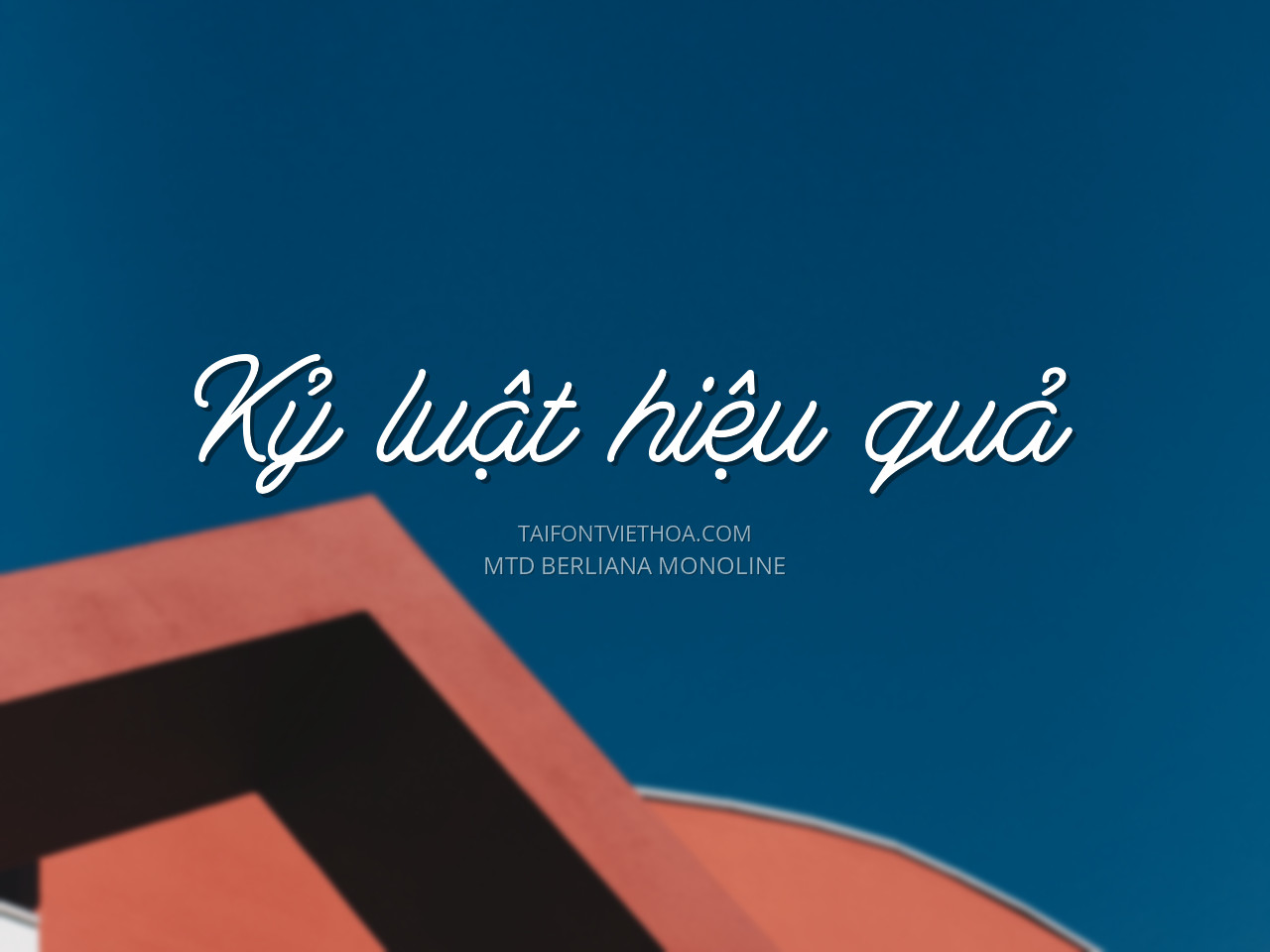
Giới thiệu về font Berliana Monoline – Thanh thoát, nữ tính và đầy tính thủ công
Berliana Monoline là một kiểu chữ viết tay (monoline script) được thiết kế với phong cách tối giản và tinh tế, thể hiện qua các nét bút liền mạch, mảnh đều từ đầu đến cuối. Font mang đậm hơi thở thủ công, nhẹ nhàng và thân thiện, rất phù hợp với các thiết kế cần thể hiện sự mềm mại, cảm xúc và tính cá nhân hóa cao. Với cấu trúc rõ ràng và form chữ đẹp mắt, Berliana Monoline thường được sử dụng trong thiệp cưới, logo thương hiệu handmade, bao bì mỹ phẩm hoặc các sản phẩm dành cho nữ giới. Font hỗ trợ hệ Latin mở rộng với hơn 60 ngôn ngữ.
Phiên bản Việt hóa do Mộc Hạthực hiện đã bổ sung đầy đủ dấu tiếng Việt và các ký tự ghép, giữ nguyên nét liền mạch và tinh thần thanh lịch của font gốc. Taifontviethoa.comđã chọn lọc và chia sẻ Berliana Monoline như một lựa chọn lý tưởng cho các nhà thiết kế đang tìm kiếm một kiểu chữ viết tay nhẹ nhàng, đơn giản nhưng không kém phần duyên dáng trong truyền thông thương hiệu.
Đặc điểm monoline tinh tế và ứng dụng lý tưởng của Berliana Monoline
Berliana Monoline có cấu trúc chữ đều nét, không có sự chênh lệch giữa các nét thanh – đậm như trong thư pháp truyền thống. Các ký tự được nối liền mềm mại, có độ nghiêng vừa phải, giúp font giữ được cảm giác tự nhiên như bút tay mà vẫn đảm bảo tính rõ ràng, dễ đọc. Font đi kèm nhiều glyphs thay thế và ligatures, cho phép người dùng tạo nên layout chữ cá nhân hóa, phù hợp nhiều mục đích sử dụng.
Font phù hợp với các thiết kế như: thiệp cưới, bộ nhận diện thương hiệu mỹ phẩm thủ công, logo spa, thư mời sự kiện, blog cá nhân, nhãn sản phẩm handmade hoặc bao bì thực phẩm organic. Ngành nghề lý tưởng gồm: thiệp cưới – ảnh cưới, thời trang nữ, mỹ phẩm thiên nhiên, spa – chăm sóc sắc đẹp, sản phẩm thủ công, thiết kế cảm xúc hoặc thương hiệu hướng tới sự tinh tế và nữ tính.